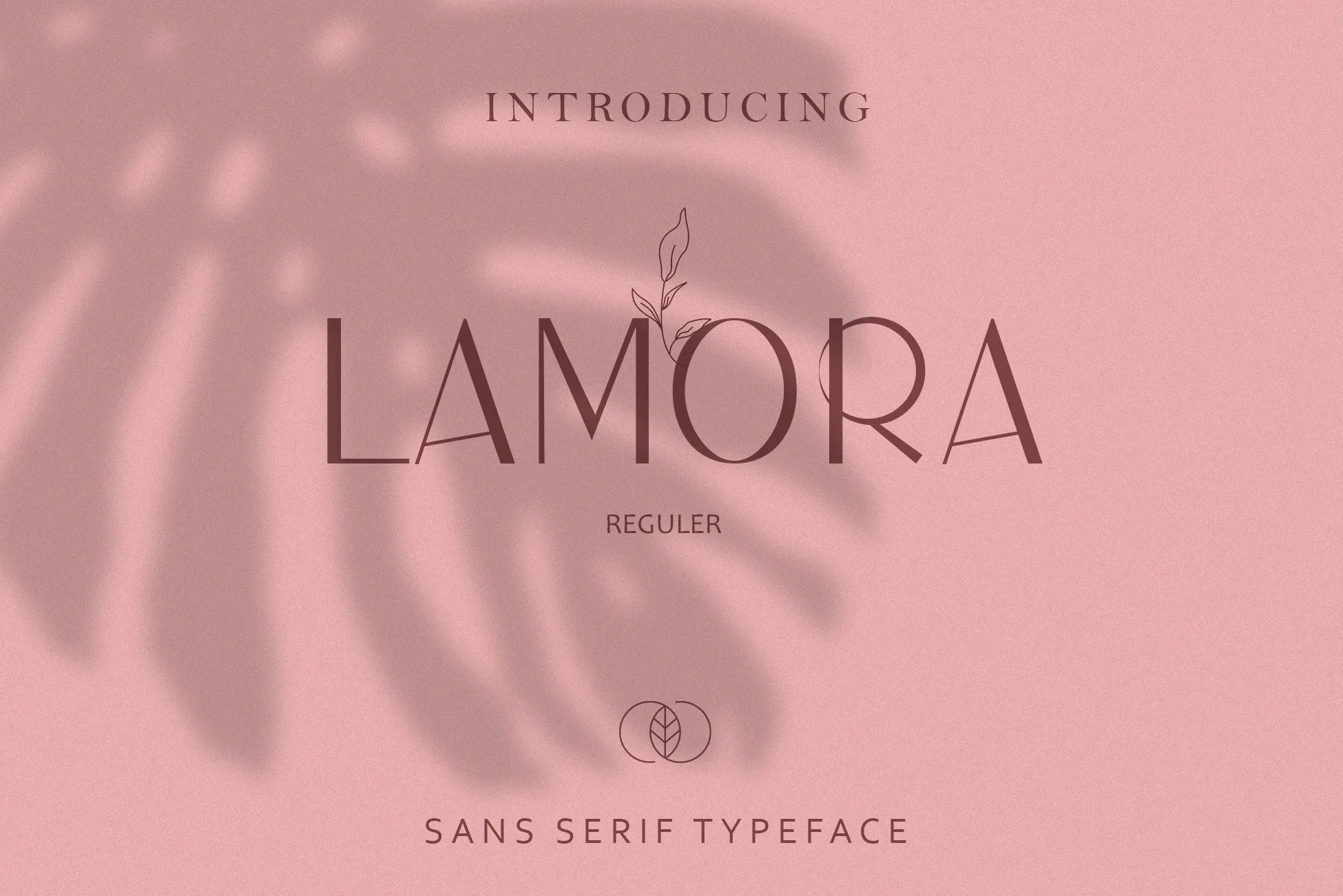
Lamora Font – Fonte Grátis
Lamora Font
A Lamora Font é uma escolha perfeita para designers que procuram um estilo moderno e clean sem serif. Criada pelo talentoso Andri nayoan, esta fonte sans-serif traz leveza à qualquer projeto visual. Ela não só adicionará elegância, mas também dará um toque sofisticado ao seu trabalho de design. A Lamora é uma opção ideal para quem busca uma fonte moderna e prática que se ajusta perfeitamente a muitos formatos gráficos, garantindo um resultado profissional e impecável. Seja em logotipos, banners ou aplicativos digitais, ela estará sempre ao seu lado, adicionando um toque de luxo a cada criação. Experimente a Lamora hoje e veja por si mesmo o encanto que esta font pode trazer para seus projetos!